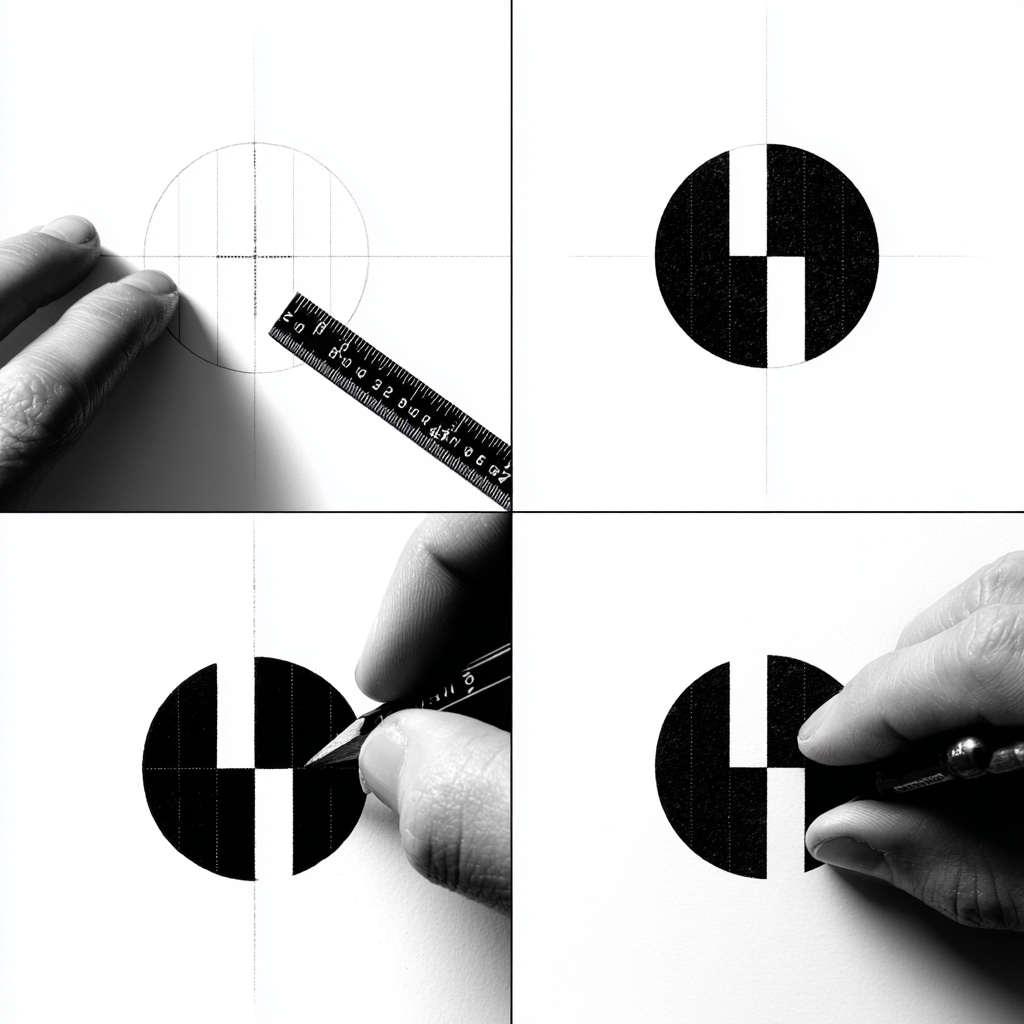
디자인 전문가가 없더라도 로고를 만들 수 있을까요? 요즘은 AI와 다양한 온라인 툴 덕분에, 디자인 경험이 전혀 없어도 누구나 로고를 만들 수 있는 시대예요. 자신만의 브랜드를 시작하려는 분들이라면 이 질문 한번쯤 해봤을 거예요.
제가 생각했을 때, 디자이너 없이 로고를 만든다는 건 단순한 비용 절감의 문제가 아니라 ‘나만의 브랜드를 직접 만들어가는 즐거움’에 더 가까운 일이에요. 하지만 아무 준비 없이 시작하면 시간도 많이 걸리고, 결과물도 기대에 못 미칠 수 있죠.
그래서 오늘은 2025년 현재, 디자이너 없이도 현실적으로 멋진 로고를 만들 수 있는 방법과 실전 팁을 아주 자세히 소개해볼게요. AI 도구, 템플릿, 무료 리소스까지 전부 알려줄게요! 🎨✨
이제 본격적으로 하나하나 알아볼까요? 각 단계마다 필요한 정보, 추천 도구, 실제 사용 사례까지 꼼꼼히 알려줄 테니 따라오기만 하면 돼요! 😉
🎨 로고 디자인의 필요성과 배경
로고는 브랜드의 첫인상을 결정짓는 가장 중요한 시각 요소예요. 실제로 소비자는 로고만 보고 브랜드의 신뢰도를 판단하거나, 기억 여부를 결정하기도 해요. 우리가 유명 브랜드를 떠올릴 때, 가장 먼저 떠오르는 것도 대부분 그 로고 모양이잖아요.
특히 1인 창업자나 소규모 비즈니스에게 로고는 단순한 이미지가 아니라 정체성을 나타내는 상징이에요. SNS 프로필 사진, 명함, 포장지, 웹사이트, 프레젠테이션 등 거의 모든 곳에 사용되기 때문에 빠르게 만들어두는 것이 좋아요.
과거에는 로고를 만들기 위해서는 전문 디자이너를 고용하거나 디자인 스튜디오에 맡겨야 했지만, 지금은 상황이 완전히 달라졌어요. 온라인 툴, AI 로고 생성기, 템플릿 기반의 서비스가 다양하게 나와있어 누구나 로고를 직접 만들 수 있게 되었어요.
이러한 변화는 특히 예산이 한정된 초기 창업자에게 큰 도움이 되고 있어요. 직접 로고를 만드는 과정에서 자신의 브랜드를 더 깊이 있게 이해할 수 있고, 결과물에 애정도 생긴답니다. 💡
🧠 브랜드 로고가 중요한 이유
중요 요소 설명 기억력 로고는 브랜드를 빠르게 기억시키는 도구예요. 신뢰감 전문적인 로고는 브랜드 신뢰도를 높여줘요. 정체성 로고는 브랜드의 메시지를 시각적으로 표현해요. 통일성 모든 디자인 요소에 일관성을 부여해줘요. 이렇게 로고는 단순히 ‘예쁜 이미지’를 넘어서 브랜드 전략 전체에 영향을 주는 핵심 요소예요. 그래서 ‘디자이너 없이 만들기’라는 선택도 결코 가볍게 보면 안 돼요. 준비가 잘 되어야 좋은 결과로 이어지죠! 😊
🛠 로고 제작을 위한 온라인 툴 소개
디자이너 없이 로고를 만들려면 가장 먼저 필요한 게 바로 믿을 만한 ‘도구’예요. 요즘은 정말 다양한 온라인 로고 생성기가 있고, AI 기술이 적용돼서 몇 번의 클릭만으로도 완성도 높은 결과를 만들 수 있답니다.
그럼 지금부터 제가 엄선한 ‘사용자 친화적 로고 제작 툴’을 소개할게요! 🧰✨
🔧 추천 온라인 로고 생성기 비교표
툴 이름 특징 가격 사용 난이도 추천도 Canva 드래그 앤 드롭, 다양한 템플릿 기본 무료, Pro 유료 하 ★★★★★ Looka AI 로고 자동 생성 패키지 구매 중 ★★★★☆ Wix Logo Maker 웹사이트 제작과 연동 유료 중 ★★★☆☆ Hatchful 쇼핑몰에 적합, 무료 제공 무료 하 ★★★★☆ 도구는 많지만, 가장 중요한 건 나에게 맞는 플랫폼을 찾는 거예요. 쉽게 수정이 가능하고, 나중에 브랜드 확장에도 잘 어울릴 수 있도록 유연한 디자인 시스템을 갖춘 곳을 고르면 좋아요! 👍
🧩 셀프 로고 제작 절차
디자이너 없이 직접 로고를 만들기로 했다면, 이제 중요한 건 ‘어떻게 시작할지’예요. 막연하게 툴만 열어놓고 디자인을 시작하면 오히려 더 헤맬 수 있어요. 그래서 로고 제작도 단계별로 체계적으로 접근하는 게 필요해요. 🎯
첫 단계는 브랜드 콘셉트 정리예요. 로고는 결국 브랜드의 상징이기 때문에, 브랜드가 어떤 이미지를 전달하고 싶은지, 어떤 고객층을 겨냥하고 있는지를 먼저 정리해야 해요. 예를 들어 젊고 캐주얼한 브랜드라면 부드러운 곡선과 생동감 있는 컬러가 잘 어울리죠.
그다음은 키워드 도출이에요. 브랜드의 특징을 떠올릴 수 있는 단어나 문장을 정리해보는 거예요. ‘자연’, ‘에너지’, ‘전문성’, ‘소프트함’ 등 키워드를 뽑아두면 나중에 아이콘, 폰트, 색상 선택에 큰 도움이 돼요.
이제 본격적인 디자인 단계예요. 앞에서 추천한 온라인 툴에 들어가서, 브랜드 이름을 입력하고 키워드 기반 템플릿을 선택하면 AI가 다양한 시안을 제시해줘요. 여기서 마음에 드는 스타일을 선택한 뒤, 색상과 폰트를 조절해서 나만의 로고로 완성해요!
📌 셀프 로고 제작 단계 요약
단계 설명 1단계 브랜드 콘셉트 정리 2단계 핵심 키워드 선정 3단계 툴 선택 및 시안 생성 4단계 디자인 수정 및 저장 마무리 단계에서는 다양한 상황에 맞게 로고를 저장하는 게 중요해요. 흑백 버전, 투명 배경 버전, 정사각형 버전 등 다양한 형태로 파일을 만들어두면 SNS, 웹사이트, 인쇄물 등 어디에서든 유용하게 쓸 수 있어요.
🪄 비전문가 제작의 장점과 한계
로고를 직접 만든다는 건 매력적인 일이에요. 시간과 비용을 아끼는 건 물론이고, 브랜드에 대한 애정이 더 깊어지기도 하거든요. 그런데 과연 비전문가가 만든 로고가 정말 ‘괜찮을까?’라는 질문이 생기기도 하죠. 🤔
우선 가장 큰 장점은 '비용 절감'이에요. 전문 디자이너에게 로고를 맡기면 수십만 원에서 많게는 수백만 원까지 드는 경우도 있어요. 하지만 셀프로 만들면 대부분 무료 또는 소액의 툴 이용료만 있으면 끝이에요.
또 하나는 '즉시성'이에요. 디자인 업체에 맡기면 상담, 시안 조율, 수정 등 시간이 오래 걸리지만, 셀프 제작은 마음만 먹으면 당일에도 로고 완성이 가능하죠. 빠르게 움직이는 스타트업이나 1인 브랜드에는 큰 장점이에요.
하지만 단점도 있어요. 대표적인 건 '브랜드 일관성'이 무너질 수 있다는 거예요. 전문 디자이너는 브랜드의 색상 시스템, 폰트 규칙, 사용 가이드를 함께 설계하지만 셀프 제작은 보통 이런 부분이 빠지기 쉬워요.
⚖ 장점 vs 단점 비교표
구분 장점 단점 비용 디자인 비용이 거의 없음 고퀄리티 작업은 어려움 속도 즉시 제작 가능 전략적 기획 부족 자율성 내가 원하는 대로 디자인 가능 디자인 전문성 부족 따라서 가장 좋은 방법은 ‘기본은 직접 만들되, 중요한 시점에는 전문가 검토를 받는 것’이에요. 초반에는 셀프 로고로 시작하되, 브랜드가 성장하면 전문가의 손을 한번 빌리는 것도 충분히 좋은 선택이죠. 😊
💡 초보자를 위한 실전 팁
로고를 처음 만드는 분들은 어디서부터 시작해야 할지 막막할 수 있어요. 그래서 오늘은 초보자도 바로 실천할 수 있는 실전 팁들을 소개할게요. 이 팁들만 잘 따라도 로고 퀄리티가 한층 업그레이드된답니다! 🚀
첫 번째는 ‘단순하게 시작하라’는 원칙이에요. 초보자일수록 여러 아이디어를 한꺼번에 넣으려는 경향이 있는데, 이는 로고의 전달력을 떨어뜨려요. 성공적인 로고는 대부분 심플하면서도 강한 인상을 주는 특징이 있어요.
두 번째는 컬러 선택이에요. 초보자라면 ‘두 가지 색상’만 사용하는 걸 추천해요. 너무 많은 색을 쓰면 조화가 깨지고, 인쇄나 다양한 매체에서 표현이 어렵거든요. 색상은 브랜드 성격을 가장 잘 표현하는 요소 중 하나예요.
세 번째는 폰트에 집중하기예요. 로고에서 폰트는 분위기를 좌우해요. 세리프(Serif) 폰트는 전통적이고 고급스러운 느낌, 산세리프(Sans-serif)는 깔끔하고 현대적인 느낌을 줘요. 너무 개성 강한 폰트는 피하는 게 좋아요.
📝 실전 디자인 팁 요약표
카테고리 실천 팁 디자인 단순하고 명확한 형태로 구성 색상 주조색 1개 + 보조색 1개 활용 폰트 읽기 쉬운 폰트 사용 형태 정사각형이나 원형 안에 구성 추천 마지막 팁은 ‘사용 환경을 고려하라’예요. 로고는 온라인에서만 쓰이지 않아요. 인쇄물, 간판, 모바일 등 다양한 환경에서 동일하게 잘 보여야 해요. 따라서 너무 얇은 선이나 복잡한 요소는 피하는 게 좋아요.
🧪 실제 셀프 제작 사례 분석
이제 실제로 디자이너 없이 로고를 만든 사례들을 살펴보면서, 어떤 전략이 효과적이었는지 알아볼게요. 다양한 업종의 셀프 로고 제작 사례를 보면, 직접 만들 때 어떤 방향으로 가야 할지 감이 잡힐 거예요. 💼
첫 번째 사례는 1인 쇼핑몰 ‘달곰상점’이에요. 이 브랜드는 감성 굿즈를 판매하는 온라인 상점으로, 로고 역시 감성적인 느낌을 강조했어요. Canva를 활용해 연한 핑크톤의 심볼과 손글씨 느낌의 폰트를 사용해 따뜻한 느낌을 주고 있답니다.
두 번째 사례는 스타트업 ‘BitMind’예요. 기술 기반의 AI 서비스를 제공하는 기업인데, Looka를 통해 모던하고 날카로운 이미지의 로고를 만들었어요. 블루 계열 색상에 기하학적인 마크를 활용해서 전문성과 미래지향적 느낌을 살렸죠.
세 번째는 지역 소상공인 ‘콩나물국밥집’이에요. Hatchful을 활용해 전통적인 서체와 함께 국밥 뚝배기 모양 아이콘을 사용했어요. 재미있는 건, 메뉴 사진과 로고를 일관된 색감으로 구성해서 SNS에서도 통일감 있게 브랜드가 인식되더라고요! 🍲
📊 실제 사례별 전략 요약
브랜드명 도구 전략 특징 달곰상점 Canva 감성 강조 손글씨+파스텔톤 BitMind Looka 기술적 이미지 블루 계열+기하학 콩나물국밥집 Hatchful 전통적 정체성 국밥 아이콘+서체 통일 이처럼 성공적으로 셀프로 로고를 만든 사례들은, 단순히 툴만 잘 썼기 때문이 아니에요. 브랜드의 방향성과 메시지를 명확히 하고, 그것을 시각적으로 어떻게 풀어낼지 고민한 결과라는 거예요. 🌈
Q4. 로고를 만들고 나서 색상 가이드는 어떻게 설정하나요?
A4. 로고를 만든 후에는 사용된 색상의 HEX 코드나 RGB 값을 따로 기록해두는 게 좋아요. 이후 웹, 인쇄 등 다양한 매체에서 동일한 톤을 유지할 수 있어요.
Q5. 모바일 환경에서도 로고가 잘 보이게 하려면 어떻게 해야 하나요?
A5. 복잡한 요소를 줄이고, 폰트는 두껍고 선명한 걸 사용해요. 배경과 대비가 강한 색상을 사용하면 작게 보여도 인식이 잘 돼요.
Q6. 만든 로고를 인쇄물에 쓸 수 있나요?
Q7. 로고에 아이콘을 꼭 넣어야 하나요?
A7. 꼭 그렇진 않아요. 텍스트만으로도 충분히 멋진 로고가 될 수 있어요. 하지만 브랜드 성격을 직관적으로 표현하고 싶다면 아이콘도 효과적이에요.
Q8. 나중에 로고를 바꿔도 되나요?
A8. 물론이죠! 브랜드가 성장하면서 리브랜딩은 자연스러운 일이에요. 다만 기존 로고와 너무 동떨어지지 않도록 변화의 폭을 조절하는 게 좋아요.